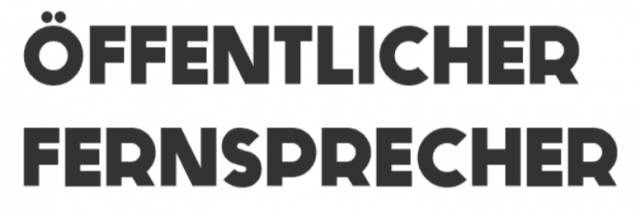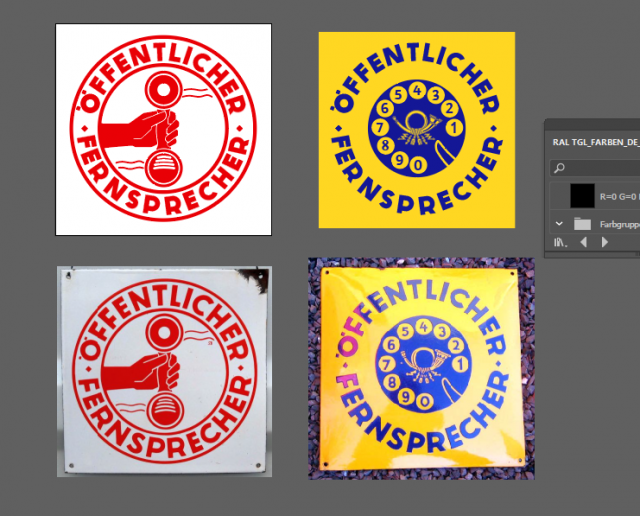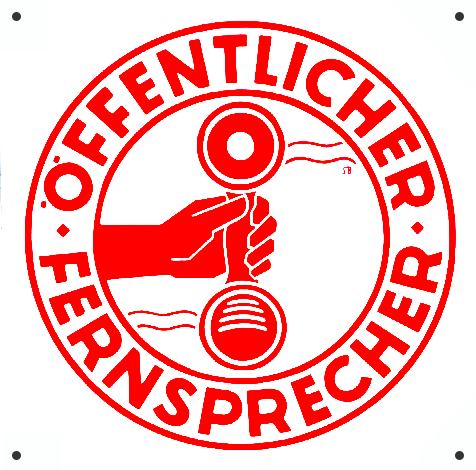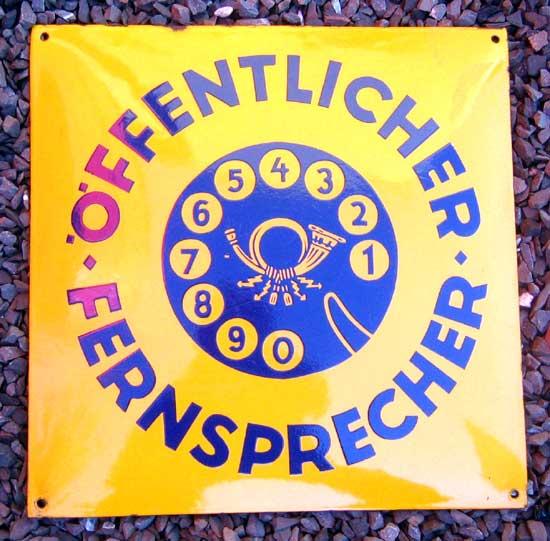
Alte Telefonzellen-Schrift
@catfonts Hallo Peter würde das als Nachbau durchgehen auf dem ersten Blick? ok die Trennungspunkte müssten noch verschoben werden.
Das kommt natürlich sehr drauf an, wofür man das einsetzt. Im Original sind die Buchstaben ja gewissermaßen rundgedengelt. Das funktioniert natürlich bei Schrift an den Kreis auszurichten nicht perfekt.
Ich weiß jetzt nicht, welches Grafikprogramm das hin bekommt, den Text erst in Kurven konvertieren, und dass dann um die Kreisform biegen, Möglicherweise ja mit einem 3D-Programm, indem man den Text gerade um einen Zylinder schreibt, den Text in Vektoren wandelt, und dann den Zylinder in einen Kegelstumpf wandelt, den man schattenfrei beleuchtet glatt von Oben betrachtet.
du meinst, dass die Schriften zum Zentrum hin schmaler werden, richtig? sind eher für 3d sachen gedacht und eventuell auch für wikipedia, die ja gern svg sehen. Vermutlich kann das auch Illustrator aber da müsste man jeden buchstaben in einer hüllkurve deformieren.